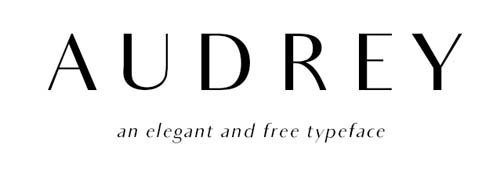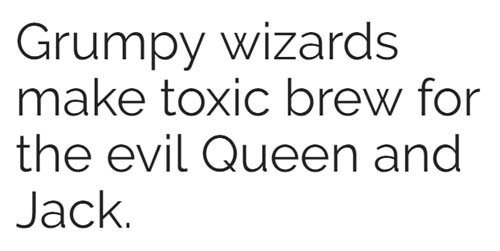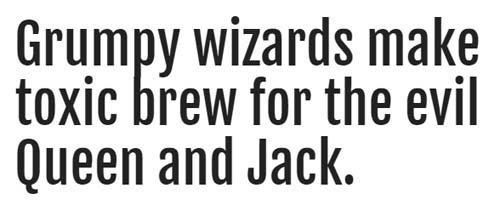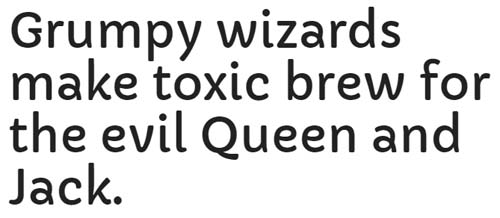
30+ Font Sans Serif Terbaik Untuk Heading Website
30+ Font Sans Serif Terbaik Untuk Heading Website – Dalam web desain font berperan sangat penting, karena meskipun desain web Anda sudah elegan tapi tidak di padu dengan font yang sesuai akan menjadikan web terlihat buruk. Kadang-kadang desain web yang sederhana dan bersih akan terlihat menarik dilihat karena penggunaan font yang pas dan menarik. Jadi salah satu solusi sederhana untuk menjadikan situs Anda terlihat menarik adalah dengan mencoba font unik untuk header Anda, buat header situs Anda menggunakan font yang berbeda dengan jenis font untuk bagian lain.
Berikut saya akan memberikan daftar 30+ font sans serif yang bisa Anda pilih untuk digunakan disitus Anda untuk heading. Tapi sebelumnya saya akan memberikan sedikit panduan cara mudah menambahkan font khusus bagi Anda pengguna WordPress.
30+ Font Sans Serif Terbaik untuk Website :
1. Bebas Neue
Bebas Neue adalah font dari keluarga sans serif yang cukup populer dan terbaik – karena begitu populernya font ini sampai-sampai penciptanya tidak takut untuk menyebutnya sebagai “Helvetica of the free font”, font jenis ini memiliki 5 style font yaitu thin, light, book, regular dan bold. Font ini terlihat sangat tegas dan akan cocok tampil sempurna untuk setiap post dan judul.
2. Aileron
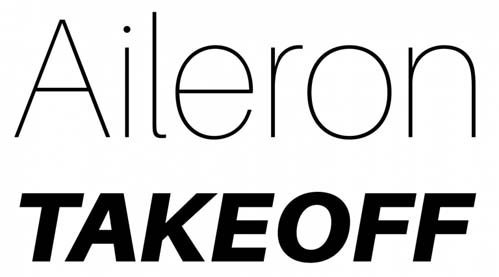
Aileron tersedia dalam sepuluh gaya yang berbeda, mulai dari ultra-tipis sampai font bold. Huruf terlihat agak kental, singkat, kekar dan padat. Font jenis ini juga akan cocok untuk bagian judul disitus anda dan ini juga merupakan Font Sans Serif Terbaik Untuk Heading Website.
3. Simplifica
Simplifica adalah font sans serif gratis yang didesain oleh KAIWA dengan huruf yang tipis dan dan tidak begitu lebar. Font ini dibuat dengan tujugan untuk menarik mata pembaca terfokus pada bagian judul.
4. Corbert Condensed Italic
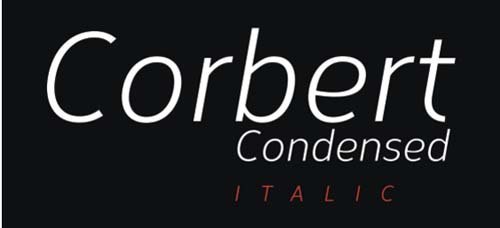
Seperti namanya, font ini adalah versi kental dari font Corbert original, dengan huruf yang agak mirip daripada font induknya. Ini cocok dan cukup baik untuk setiap desain yang memerlukan sedikit tambahan sisi berat desain.
5. Baufra
Font Baufra merupakan bagian dari font sans serif dengan desaing yang dipengaruhi oleh orang-orang dari awal abad 20. Ini menggabungkan desain geometris dengan garis-garis halus, menghasilkan efek yang sangat menyenangkan. font datang dalam enam bentuk yang berbeda dan kerning yang dapat diedit secara manual.
6. Bitner
Menurut penciptanya, desain font ini terinspirasi oleh gerakan cryptocurrency. Ini adalah jenis huruf yang agak geometris, dengan lengan pendek dan menonjol, dan datang dalam tujuh variasi yang berbeda dengan beberapa fitur OpenType.
7. DyeLine
DyeLine adalah font dengan desain geometris yang berbeda, terinspirasi oleh garis yang bersih dari gambar arsitektur dan blueprint. Font ini terasa kental, tinggi dan tipis membuat font ini terlihat bersih dan modern.
8. Glober
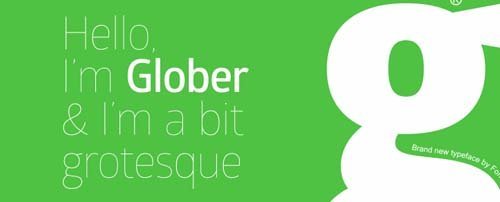
The Glober family tipografi (yang mempunyai 18 jenis ukuran berbeda) didefinisikan oleh desain geometris stylish. Mereka juga cocok untuk desain teks high-density, tapi sebagian besar akan terlihat menarik ketika digunakan untuk bagian judul.
9. Proza
Proza adalah font sans serif yang terinspirasi oleh Renaissance tipografi seperti Garamond dan Jenson. Ini diciptakan untuk bekerja dengan baik di berbagai resolusi, sehingga dapat digunakan baik untuk proyek-proyek berbasis teks dan desain besar. Perancangnya, Jasper de Waard bekerja pada jenis huruf ini selama kurang lebih dua tahun, dimulai ketika ia berusia 16 tahun (saat itu dia sudah memiliki font di Google Fonts).
10. Gentona
Gentona adalah font sans serif yang dirancang untuk digunakan di berbagai macam desain, dengan penekanan pada kepekaan kontemporer dan terinspirasi oleh tipografi aneh lainnya. Font ini membuat visual terlihat cukup mencolok.
11. Penna
Penna adalah font san serif terbaik yang unik dengan bentuk yang tipis dan guratan agak miring, ini sempurna untuk situs yang mencari jenis huruf untuk melengkapi tampilan minimalis, tapi itu juga dapat digunakan untuk efek yang besar dalam postingan.
12. Overpass
Overpass adalah font san serif terbaik dan open-source terinspirasi oleh Highway Gothic dan disponsori oleh RedHat dan orang-orang di balik distro Linux dengan nama yang sama dan juga Fedora. Ini adalah font sederhana dengan enam bobot berbeda.
13. Foobar Pro